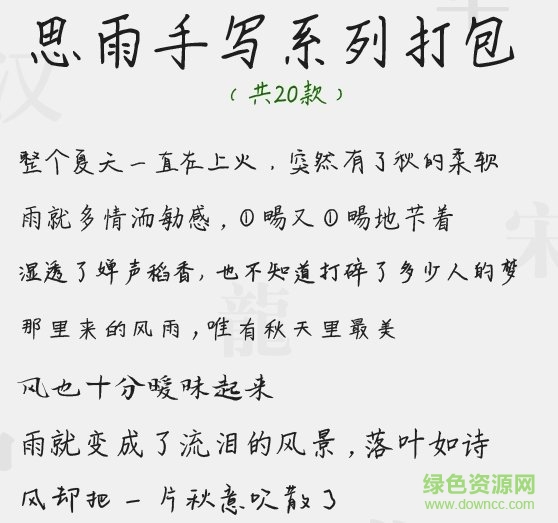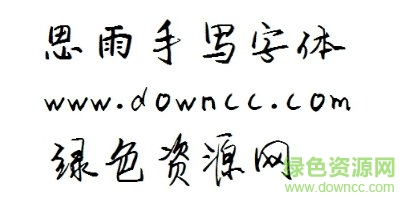
思雨手寫(xiě)系列打包
思雨手寫(xiě)字體是由思雨字庫(kù)推出一系列手寫(xiě)體打包合集,包括20款風(fēng)格獨(dú)特的思雨字體,字跡清秀舒緩,給人意境開(kāi)闊之美,喜歡的朋友就來(lái)綠色資源網(wǎng)下載使用吧!
思雨手寫(xiě)系列打包字體介紹
思雨手寫(xiě)系列收錄了20款字體,均采用了手寫(xiě)字體的風(fēng)格,給你運(yùn)筆流暢、大方清晰的視覺(jué)好感,可以運(yùn)用在書(shū)面設(shè)計(jì)、廣告策劃、海報(bào)制作等多種場(chǎng)合,給你藝術(shù)字體呈現(xiàn)的多種選擇!
思雨系列字體
手寫(xiě)體風(fēng)格特色
手寫(xiě)體是一種使用硬筆或者軟筆純手工寫(xiě)出的文字,手寫(xiě)體文字代表了中國(guó)漢字文化的精髓。這種手寫(xiě)體文字,大小不一、形態(tài)各異,在計(jì)算機(jī)字庫(kù)中很難實(shí)現(xiàn)錯(cuò)落有致的效果。只能使用手工寫(xiě)字的方法傳承下去。
手寫(xiě)體文字制作步驟
手寫(xiě)體文字是用“美工筆”在紙上寫(xiě)出來(lái)的,可能一個(gè)字會(huì)寫(xiě)幾十遍或者更多,之后再?gòu)闹虚g選出寫(xiě)的比較可以接受的拍照,上傳到電腦上用photoshop處理后制作而成。